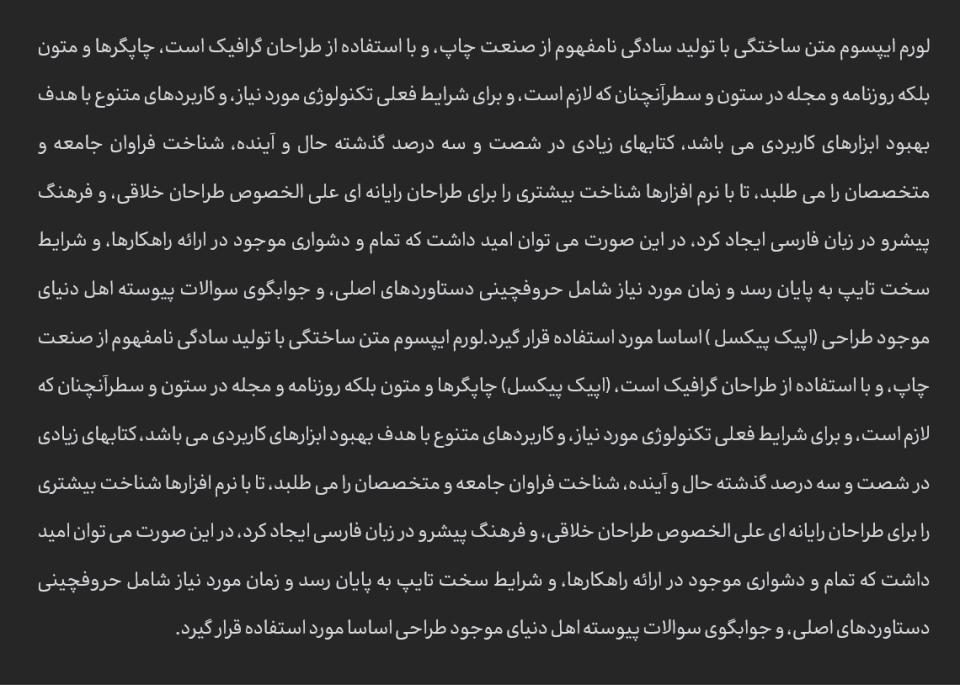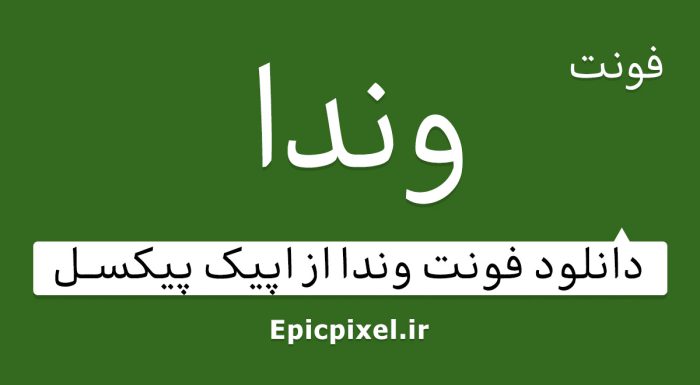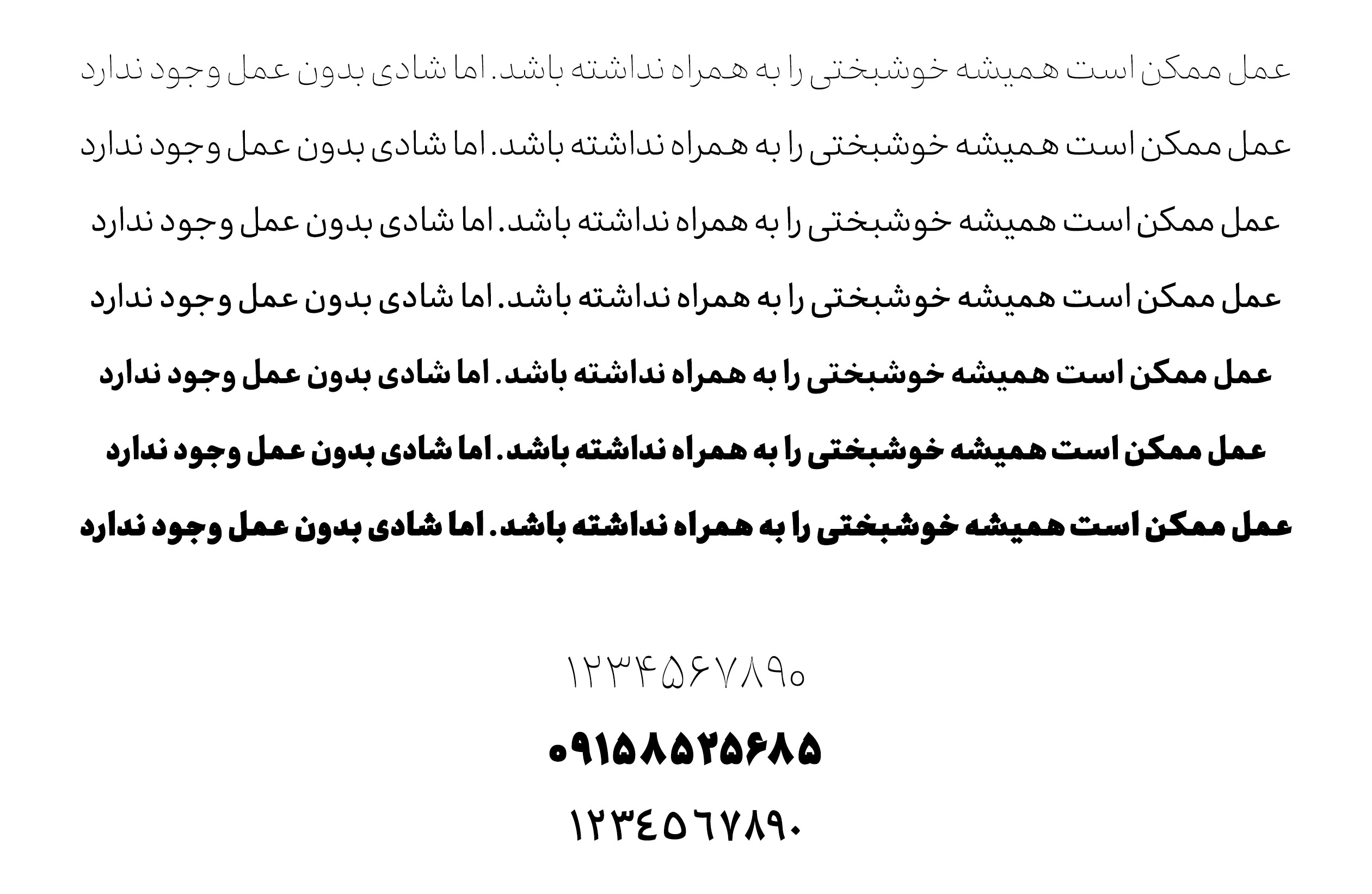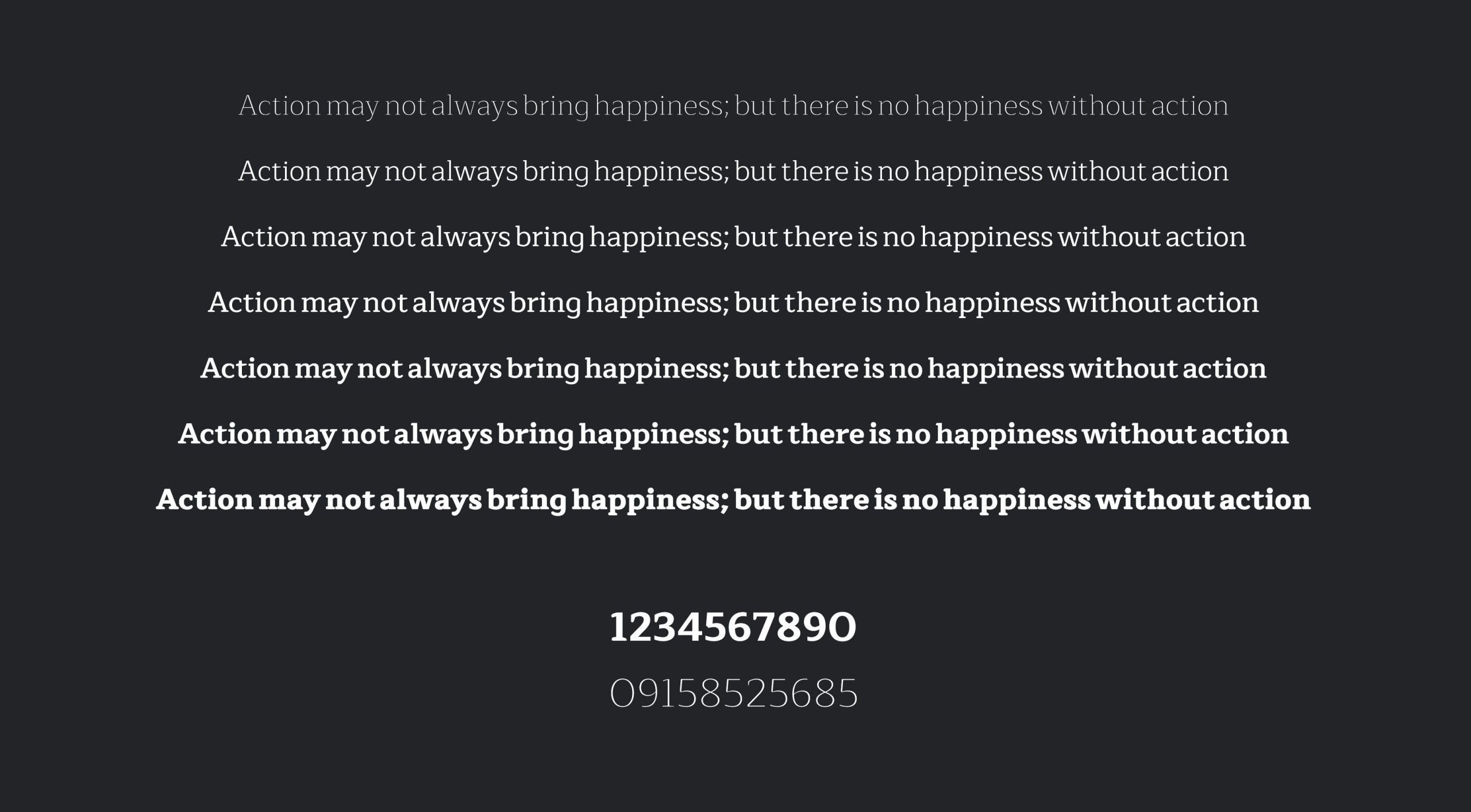
فونت وندا، یک انتخاب عالی برای کسانی است که به دنبال فونتی رسمی، خوانا و در عین حال مدرن برای نوشته های فارسی خود هستند. این فونت با الهام از فونت میترا طراحی شده و با تغییرات اساسی، ظاهری جدید و جذاب پیدا کرده است. یکی از ویژگی های برجسته وندا، ساختار رسمی و استاندارد آن است که باعث می شود برای استفاده در متون رسمی، کتاب ها، مجلات و وب سایت ها بسیار مناسب باشد. خوانایی بالای این فونت، حتی در اندازه های کوچک، تضمین می کند که مخاطب شما به راحتی مطالب را دنبال کند.
یکی دیگر از مزایای وندا، تنوع در وزن های مختلف است که به شما امکان می دهد برای هر نوع محتوایی، وزن مناسب را انتخاب کنید. این ویژگی به خصوص برای طراحان گرافیک و صفحه آراها بسیار کاربردی است. همچنین، هماهنگی بالای حروف فارسی و انگلیسی در این فونت، باعث می شود که متون شما ظاهری یکپارچه و حرفه ای داشته باشند. وندا از زبان های فارسی، عربی، کردی و اردو پشتیبانی می کند که دامنه استفاده از آن را گسترش می دهد.
با این حال، فونت وندا بدون نقص هم نیست. یکی از محدودیت های آن، عدم پشتیبانی از فونت های متغیر (Variable Fonts) است که امروزه در طراحی وب و گرافیک بسیار مورد استفاده قرار می گیرند. این موضوع می تواند برای برخی از طراحان یک نقطه ضعف محسوب شود. در مجموع، اگر به دنبال فونتی استاندارد، خوانا و با ظاهری مدرن برای پروژه های فارسی خود هستید، فونت وندا می تواند انتخاب بسیار خوبی باشد.